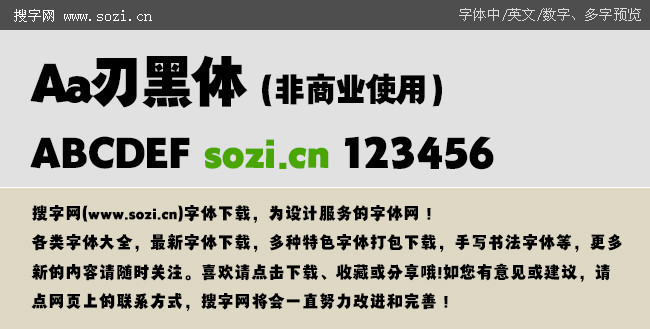
Aa刃黑體
搜字網(wǎng)給大家提供一款A(yù)a刃黑體(非商業(yè)使用)中文字體下載,該字體是一款粗體黑體字體,字體的每一個筆畫幾乎都是等寬的,給人一種非常沉穩(wěn)的視覺感受,適合書裝設(shè)計、包裝、海報設(shè)計等應(yīng)用(此字體為個人非商用版,商用可以聯(lián)系QQ:1006760504)。